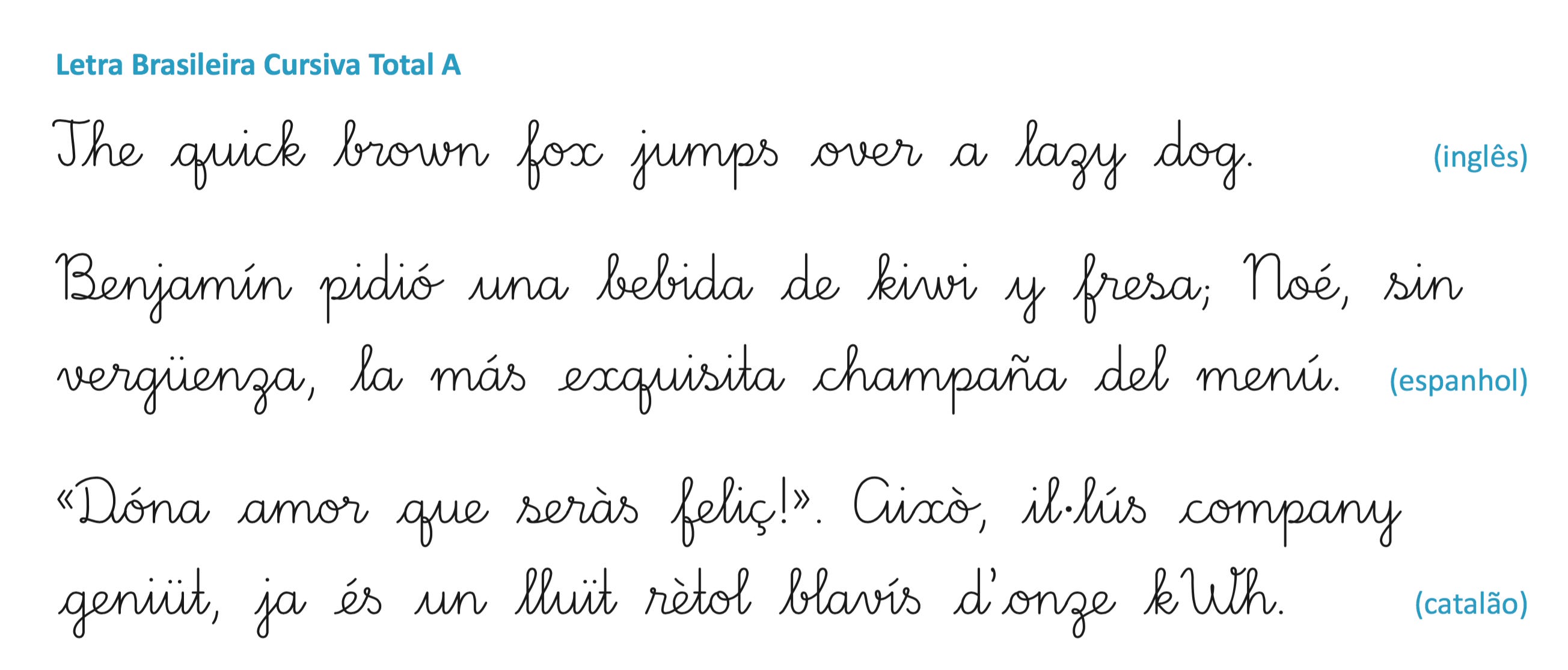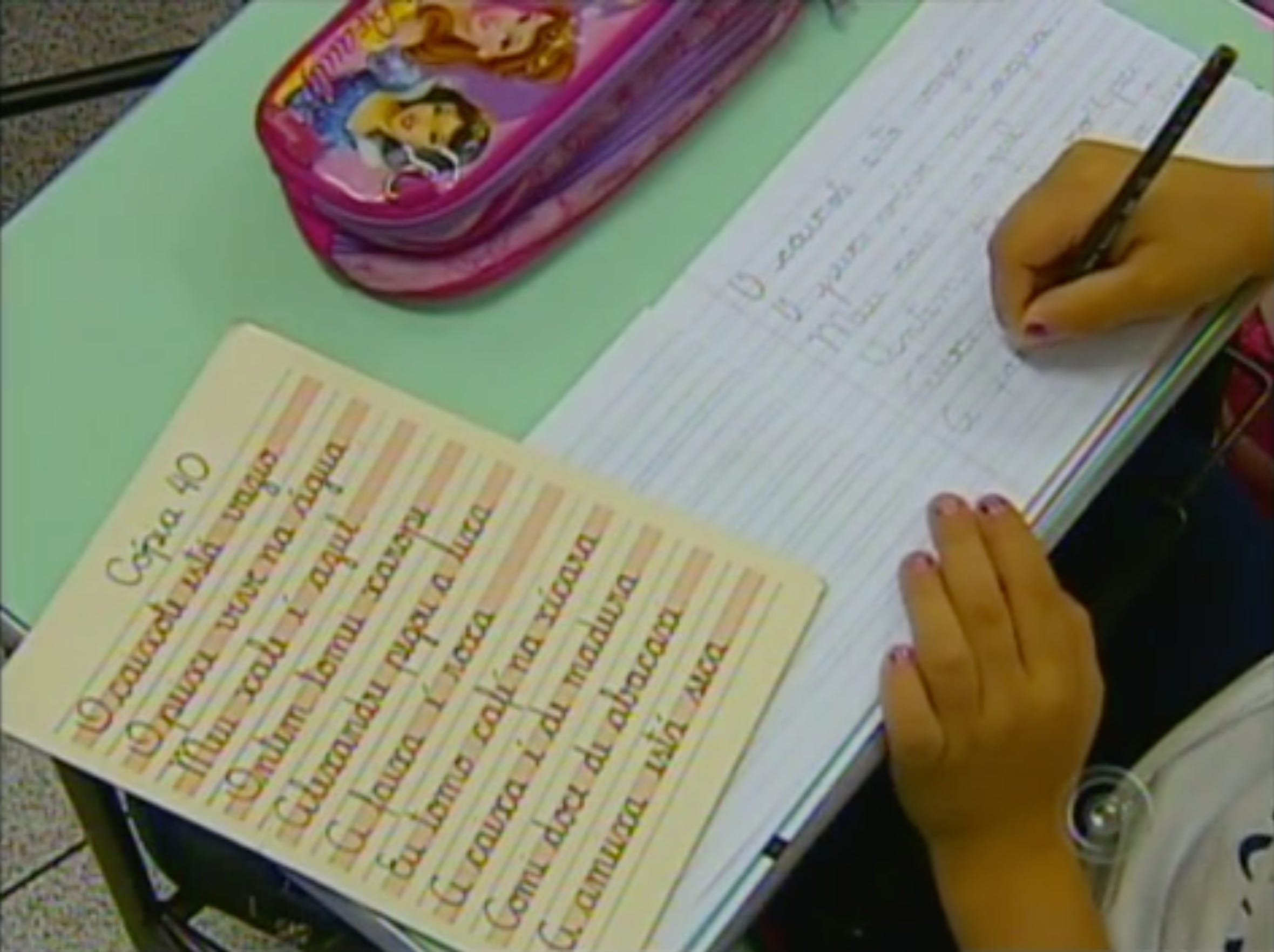
Tipo Aquilo #96 – Como se brinca com as letras
O ensino da caligrafia na infância e o universo das letras como um espaço lúdico
Uma tendência em redes sociais que começou recentemente é a das assinaturas caprichadas, daquelas que pegam uma forma de letra específica e fazem a caneta rodopiar sobre o papel tal qual um dançarino do Bolshoi. Isso resgata uma tradição antiga de assinaturas imponentes, daquelas que você tem certeza que seus pais e avós sabem o que estão fazendo no mundo quando eles empunham a caneta e marcam o papel em riscos ágeis, enquanto você custa a fazer a mesma assinatura do seu nome como estava na carteira de identidade. Eu tenha uma assinatura caprichada no passaporte, que eu treino desde os 16 anos e refinei com o que eu aprendi de caligrafia. Só que minha carteira de identidade é a memória mais remota que eu tenho da minha escrita quando criança, e eu preciso fazer esforço redobrado para escrever como naquela época, quando necessário. Obrigado pela firma reconhecida, cartórios.
Vez em quando, no Instagram ou no X Twitter, ainda apareciam algumas correntes incentivando a mostrar como é sua letra casual, algo que talvez não aconteça mais em tempos de IA generativa e uma máquina facilmente forjando sua escrita, se você der mole. Aliás, você lembra de quando e como aprendeu a escrever? Você ainda tem seus primeiros registros escritos, seu caderno de caligrafia, e os rabiscos das primeiras séries? Existe um infinito de sentimentos guardados na forma com que traçamos cada letra e entrelaçamos palavras. Gosto de acreditar que existe também uma relação entre o prazer de escrever e o ensino da escrita além de uma ferramenta de transcrição oral, mas também como um brinquedo, um material lúdico de infinitas possibilidades. É sobre isso, com um toque excepcional de pessoalidade, que o Tipo Aquilo aborda nessa edição extra.
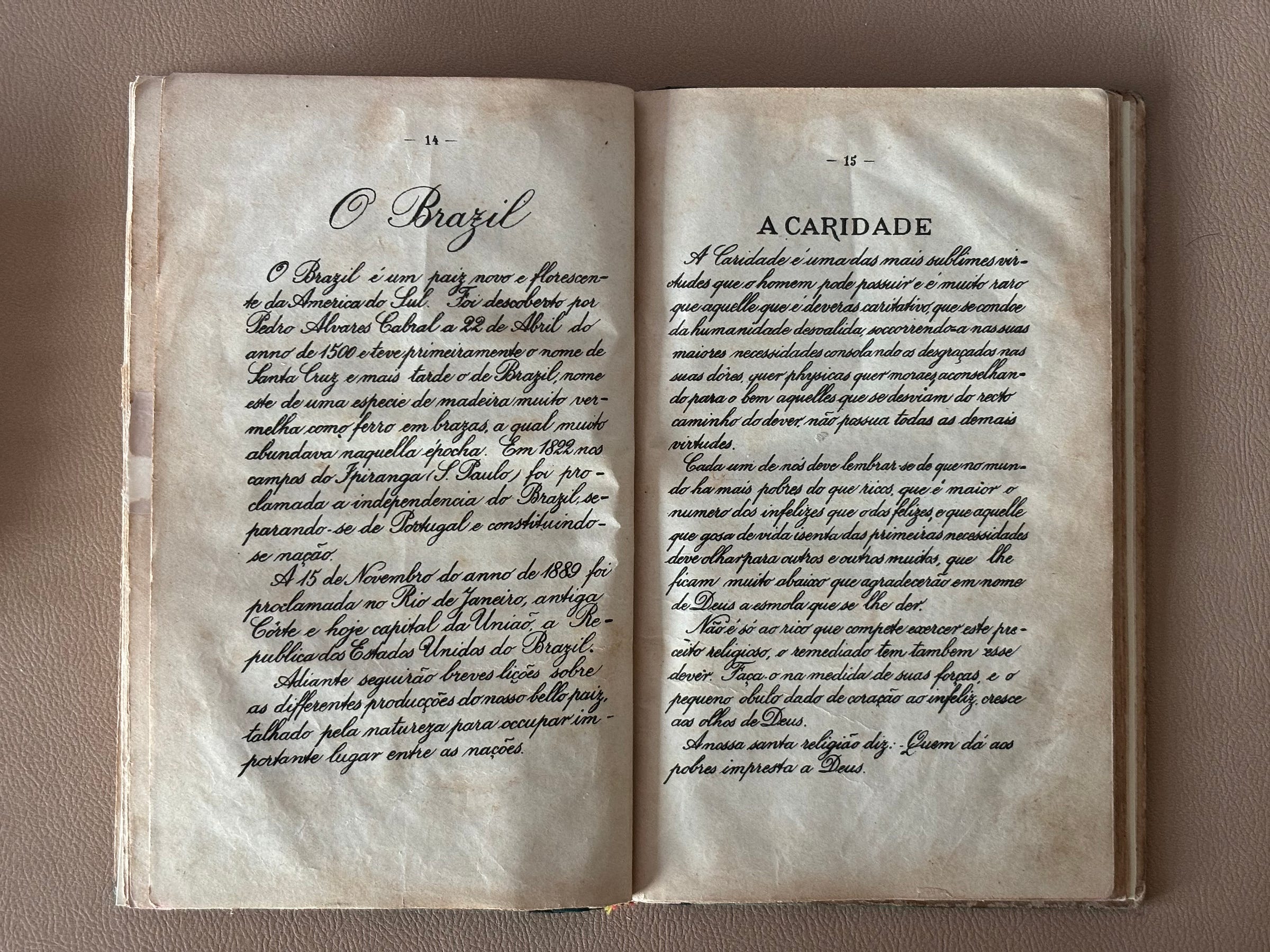
Eu tenho um caderno de caligrafia que deve ter sido feito em 1930 e alguma coisa. “Curso Graduado de Letra Manuscripta (sic)”, editado em Porto Alegre pela Selbach & Cia., um presente que guardo como um registro histórico de como as crianças brasileiras eram ensinadas a escrever. Contém exercícios de prática da mão inglesa (socorr), além de textos sobre Deus, pátria, família e tudo que uma criança da época supostamente precisava saber escrever. Contudo, a caligrafia, como ofício de criar letras bonitas, já vivia uma certa decadência; no começo do séc. XX, as tarefas mais comuns da escrita não dependiam mais de um mestre calígrafo, e algumas até podiam ser feitas usando a tipografia. Os instrumentos de escrita também se modernizaram, com o lápis e a caneta esferográfica tomando o lugar das penas. Por mais que se desejasse que o aluno aprendesse a escrever ipsis litteris aos modelos caligráficos, com o tempo, isso deixou de ser uma necessidade para a sociedade de consumo.
Já no começo do séc. XX, a tradicional mão inglesa inclinada passou a concorrer com a chamada “escrita vertical”. De origem francesa, era considerada mais fácil, econômica e recomendada por médicos-higienistas da época que viam uma correlação entre as letras inclinadas da mão inglesa e um aumento em casos de miopia entre crianças. Essa visão espalhou-se pela Europa, e obrigou os educadores ingleses a reverem sua letra de ensino, tornando-a vertical. Até o final da década de 1930, as duas escritas eram ensinadas no Brasil em estados diferentes, até a letra vertical sobressair como hegemônica. Essa “mistura” de mãos, com o tempo, virou as letras com que eu, você e nossas gerações aprenderam a escrever nossas primeiras palavras, e é “normal” que elas mudem de um estado para outro, ou de um material didático para outro, mostrando uma dificuldade em apontar como preponderante a mão inglesa vertical ou a francesa na escrita casual do brasileiro.
Os modelos de escrita usados atualmente são ainda mais “fáceis”, observando não apenas a necessidade da escrita na nossa sociedade, mas também o crescimento de uma abordagem continuada do ensinar a escrever. Em raras escolas, a escrita não é uma disciplina pontual da pré-escola, mas um conhecimento a ser refinado com o tempo, observando como cada aluno desenvolve a escrita da forma mais ágil e legível para si. A minha escrita, por exemplo, ficou mais ágil depois que eu abri mão daquele mantra de “não tirar o lápis do papel”; outras pessoas, no entanto, seguem com letras contínuas impecáveis — e eu morro de inveja de vocês. Aliás, posso assegurar que a pior época da minha escrita casual, em que eu perdi velocidade e várias explicações no quadro perderam-se ad infinitum, foi quando eu deixei minha letra parecida com a “letra de máquina”, ou “letra de bastão”, que corresponde aos desenhos comuns das fontes sem-serifa. Foram elas que os EUA tentaram ensinar em alguns estados, e eventualmente, retornaram aos modelos de caligrafia escolar tradicionais.
Outro erro da minha vida foi ter dado menos valor à poesia do que ela merece. Desde pequeno, eu já era uma criança chata “prometida” à lógica e à matemática, e isso acabou me tirando tanto o prazer de usar as palavras como brinquedo de criar versos, quanto o de usar as palavras como brinquedo de registrar e imaginar em um diário. Diário e poeminha era “pra menina”, diziam na época. Há um tempo, passou pela minha timeline o relato de uma aluna repreendida pelo professor por “perder tempo” fazendo letterings para as matérias em seu caderno, e isso me doeu, como um adulto que desenha letras e vê uma expressão criativa sendo podada a troco de nada. Aliás, até o Cadu criança-chata tinha uma pequena veia criativa pulsante, graças ao rock, o hip-hop e a cultura do graffiti, que nos anos 2000 encontraram-se no Nü Metal, algo que rende uma edição do TA por si só. Vez ou outra, algum verso de prova e última página de caderno tinha alguma “grafitada” minha, e aos poucos os amigos desenhistas de cada sala foram aparecendo e “competindo” pelos desenhos mais massa véio ao som de Linkin Park.
Antes que vocês pensem… não, eu nunca fui um grafiteiro de fato, nunca pintei uma unidade de muro. Só que, tão logo a cena do graffiti expandiu-se para além das grandes capitais, vários deles brotaram na minha quebrada natal, Taguatinga, como botões esperando a chegada da primavera. E eu ficava impressionado com a quantidade de cores e as diversas formas de brincar com letra em efeitos de volume e perspectiva, e logo queria trazer tudo isso para os humildes desenhos de letras que eu fazia. Se você pensou “hmmm, deve ter sido daí que o Cadu virou esse doido por desenhar letras”… é, pois é. Não consegui preservar nenhum desses desenhos, já que eu cresci menos apegado à minha infância do que a maioria das pessoas parecem ser.
Outra coisa que me tirou do seio da computação e me colocou nas tetas da maldade no caminho do design foram as divisórias de fichários rabiscadas com as marcas das bandas que eu gostava de ouvir, e gostava de reproduzi-las tão fielmente quanto possível. Um ensaio de alguém preocupado com branding, talvez? É difícil encontrar algum designer que não tenha tido alguma forma de expressão gráfica pessoal desde a infância. Desde o “desenhista da turma”, que geralmente fazia a camisa de formatura do terceirão, aos que se destacavam quando os trabalhos escolares envolviam alguma dinâmica de teatrinho, apresentação de slides, maquetes ou performances diversas. Feiras de Ciências eram momentos importantes para ganhar aqueles pontinhos a mais no boletim ao custo de transmitir algum conhecimento de forma criativa.
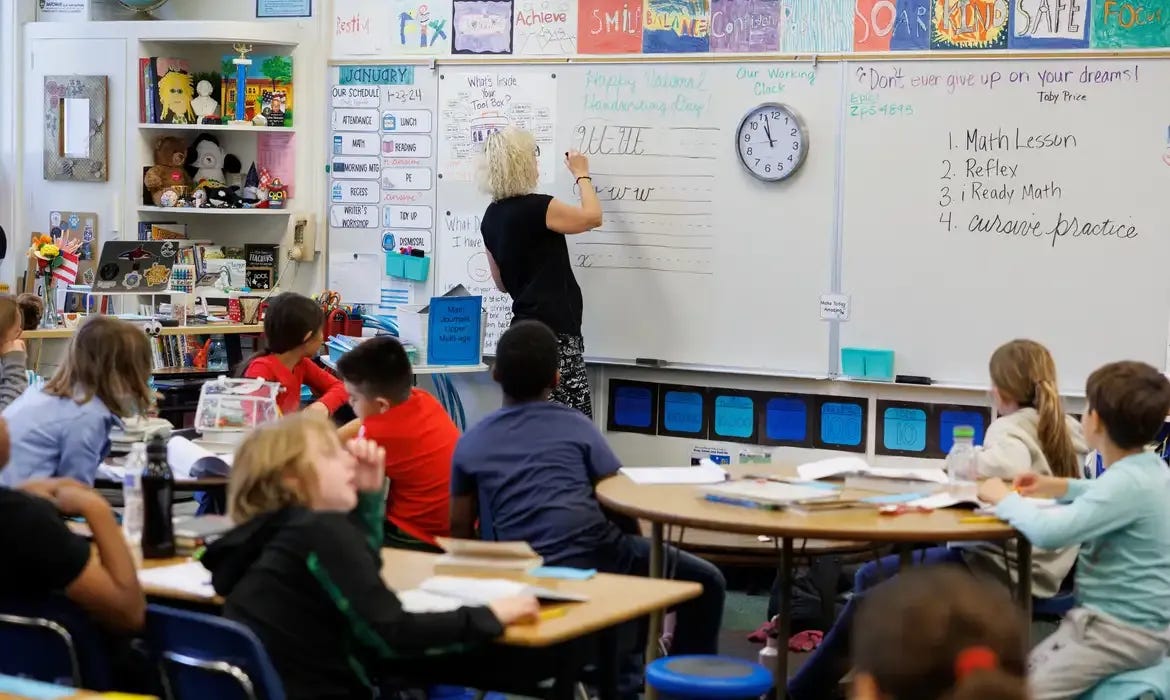
Contudo, a escola vem deixando de ser vista como um espaço lúdico, o que me preocupa bastante. Isso vem ao passo de um número grande de adultos frustrados exigindo um currículo escolar meramente utilitário, um tutorial de declarar imposto de renda, sem espaço para o desenvolvimento da criatividade. Isso nem é um problema apenas na educação pública; até nas escolas privadas, a ênfase em formar vestibulandos, ao invés de seres pensantes, tem levado a uma sociedade cada vez mais incapaz de sonhar por si e aceitar interpretações divergentes de uma literalidade normativa em diversas questões. A ausência da interpretação de texto nas redes sociais pode ser atribuída, em alguma parte, a uma vida onde só se brinca literalmente com brinquedos. Não se brinca com a comida, não se brinca com as letras, não se brinca com as roupas… e olha esse comportamento, que com Jesus, não se brinca!
🇧🇷 Fonte brazuca: Letra Brasileira, de Sandro Fetter.